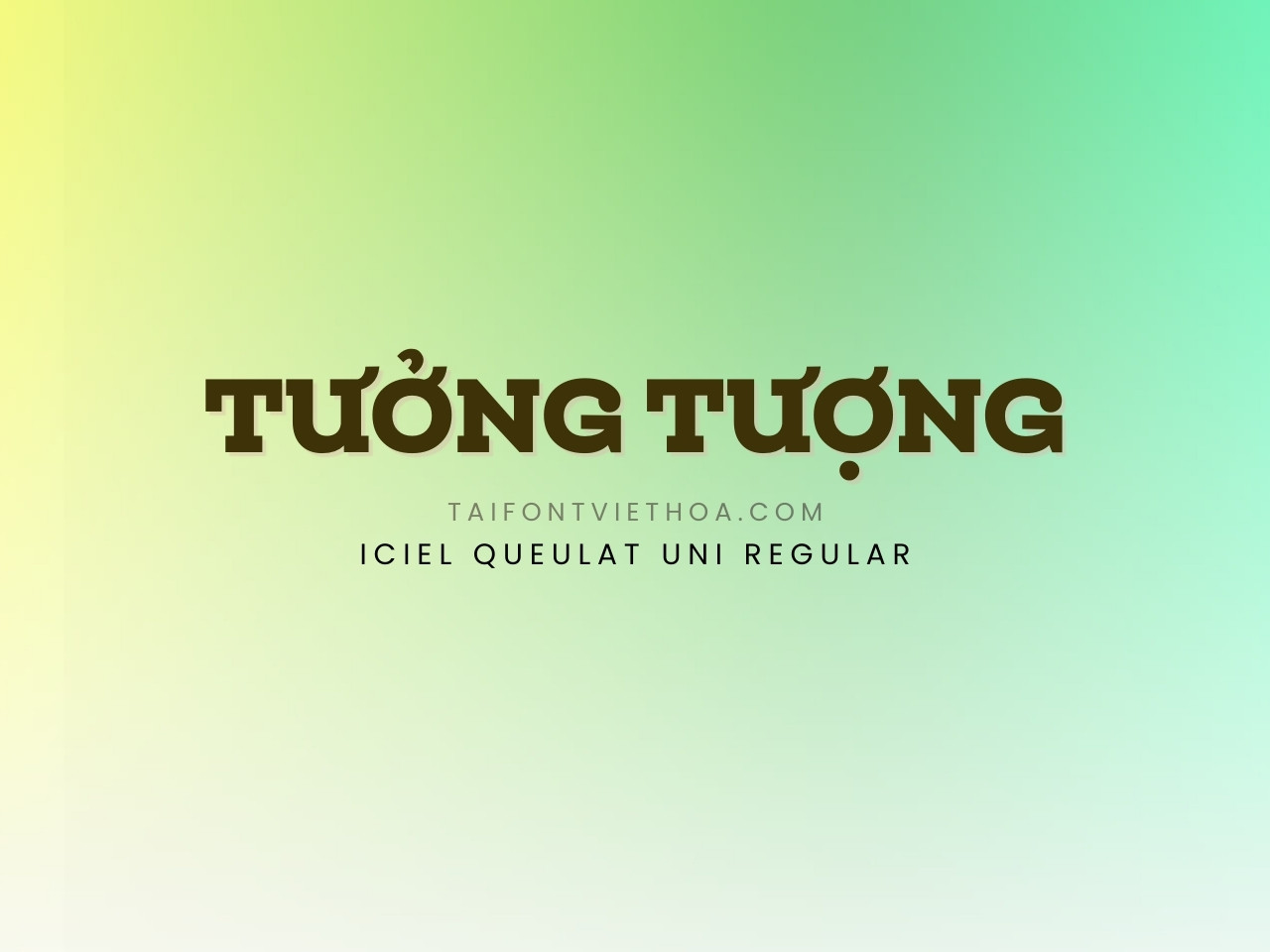
Font việt hóa iCiel Queulat Uni
Giới thiệu về font iCiel Queulat Uni – Cân bằng giữa cổ điển và hiện đại
iCiel Queulat Uni là một kiểu chữ slab serif độc đáo, nổi bật với phần chân chữ vững chắc nhưng vẫn giữ được sự mềm mại trong đường nét tổng thể. Font được Việt hóa bởi iCiel, hỗ trợ tiếng Việt đầy đủ cùng hơn 80 ngôn ngữ khác. Thiết kế gốc thuộc họ Queulat nổi tiếng bởi sự pha trộn giữa yếu tố hình học và cảm xúc, kết hợp hài hòa giữa cổ điển và hiện đại, giúp font thích nghi linh hoạt với nhiều mục đích sử dụng trong thiết kế đồ họa và thương hiệu.
Font này được taifontviethoa.com chọn lọc kỹ lưỡng và ứng dụng thực tế trong nhiều dự án sáng tạo từ in ấn đến kỹ thuật số. Với độ nhận diện cao, Queulat Uni dễ dàng tạo điểm nhấn trong thiết kế logo, tiêu đề tạp chí, banner thương hiệu hoặc giao diện kỹ thuật số có chiều sâu thị giác. Font vừa mang cảm giác chuyên nghiệp, vừa có nét thân thiện – một lựa chọn lý tưởng cho nhà thiết kế hiện đại.
Đặc điểm thiết kế và ứng dụng nổi bật của font iCiel Queulat Uni
Queulat Uni sở hữu các đặc trưng của slab serif: phần chân chữ dày, đều và chắc chắn, giúp tăng độ ổn định và độ dễ đọc. Tuy nhiên, các chi tiết bo góc nhẹ, chiều cao chữ cân đối và trọng số vừa phải đã mang lại vẻ thân thiện, linh hoạt hơn so với các font slab truyền thống. Font thể hiện tốt ở kích thước lớn, phù hợp cho tiêu đề và nhấn mạnh thông tin quan trọng.
iCiel Queulat Uni phù hợp với các lĩnh vực như công nghệ, giáo dục, bất động sản, thương hiệu thời trang hiện đại hoặc các dự án truyền thông cần sự khác biệt. Ứng dụng cụ thể gồm: thiết kế tiêu đề bài viết, nhận diện thương hiệu cao cấp, bìa tạp chí, giao diện app, bảng hiệu hoặc in ấn sáng tạo như danh thiếp – bao bì sản phẩm.